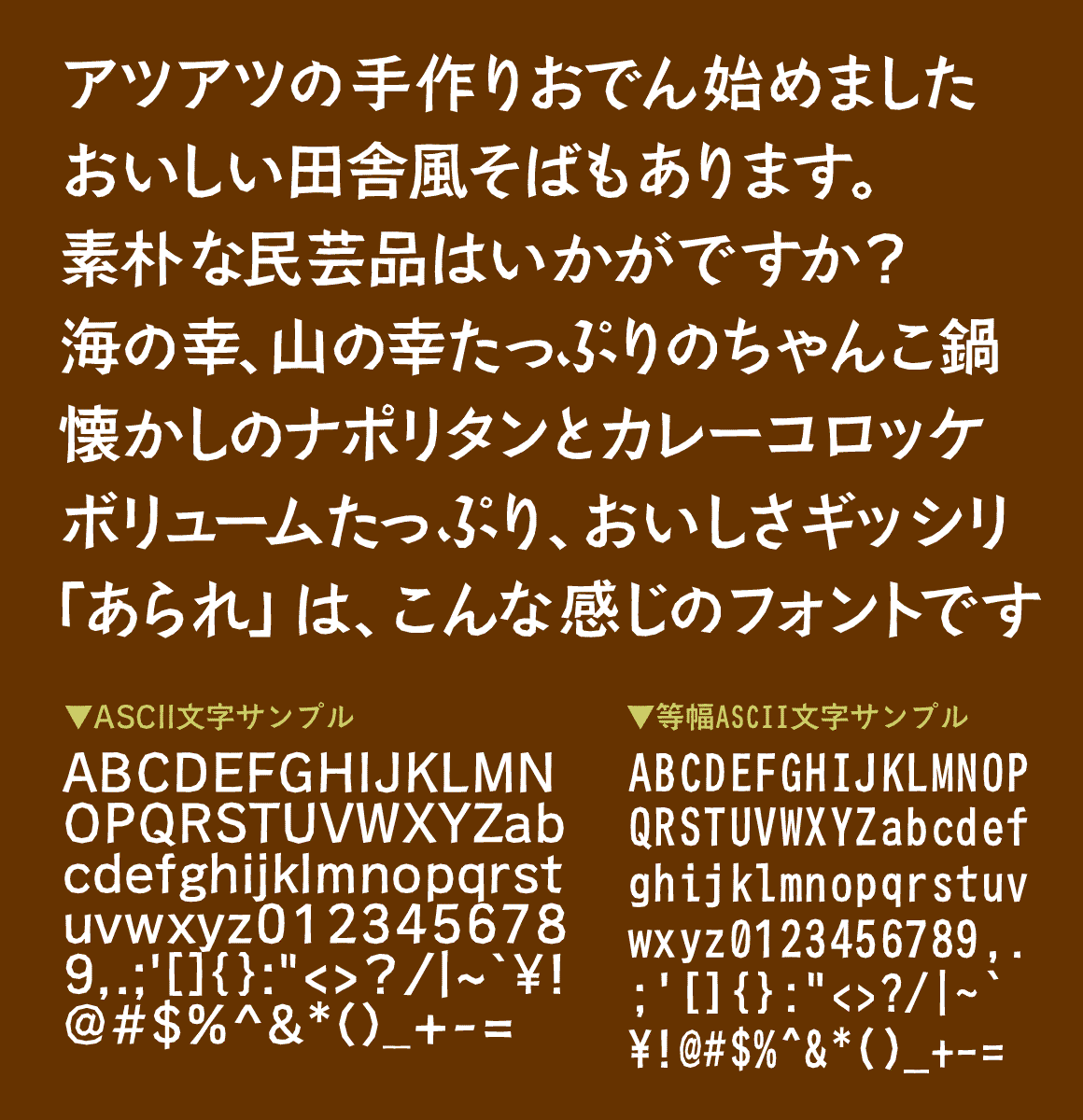
| デザイン |
切り絵や木版画のような素朴な味わいと、日本文字独特の情感を、直線だけでどのくらい表現できるか挑戦してみました
。ある程度、大きく使ってほしい書体です。小さいサイズではこの書体の面白さが発揮できません。 幼いころの記憶、懐かしい風景、手作りのぬくもり…などを、この書体で伝えてください。 2006年6月に追加された等幅バージョンは、英大文字のアイ「I」と英小文字のエル「l」数字のいち「1」や、英大文字のオー「O」と数字のゼロ「0」がはっきり区別がされているので、URL表記やプログラム編集などにぴったりです。 |
連想されるイメージ 寄せられたコメントから抜粋 |
素朴・伝統工芸・田舎・温かい・古風・味がある・懐かしい・小気味良い・和風・ハートフル・見た目スッキリ・優しい日本の風情・季節なら冬、色なら焦げ茶、酒なら焼酎・おいしそう・ほのぼの・日本昔話・寂しさ・あっさり・田舎の母・絵になる・手作り・庶民的・明治・大正ロマン作品に登場する女性たち…。 |